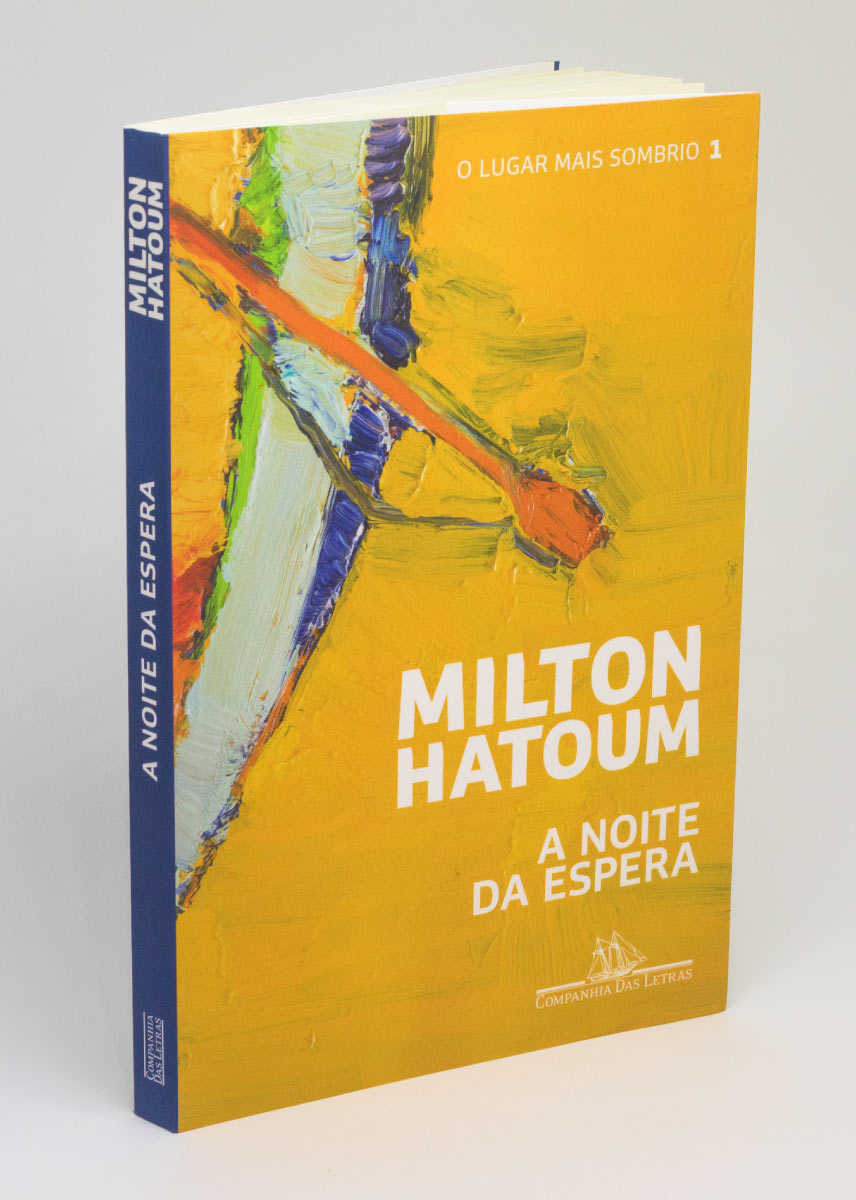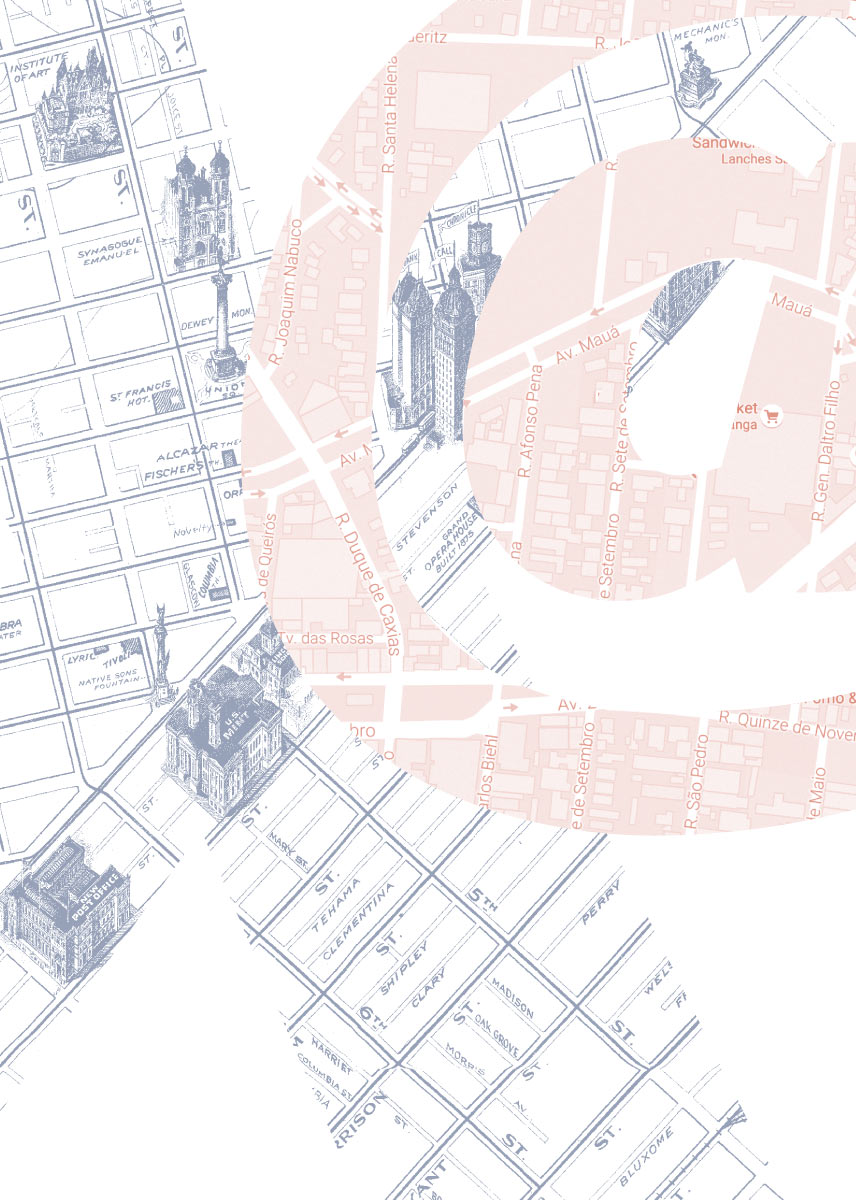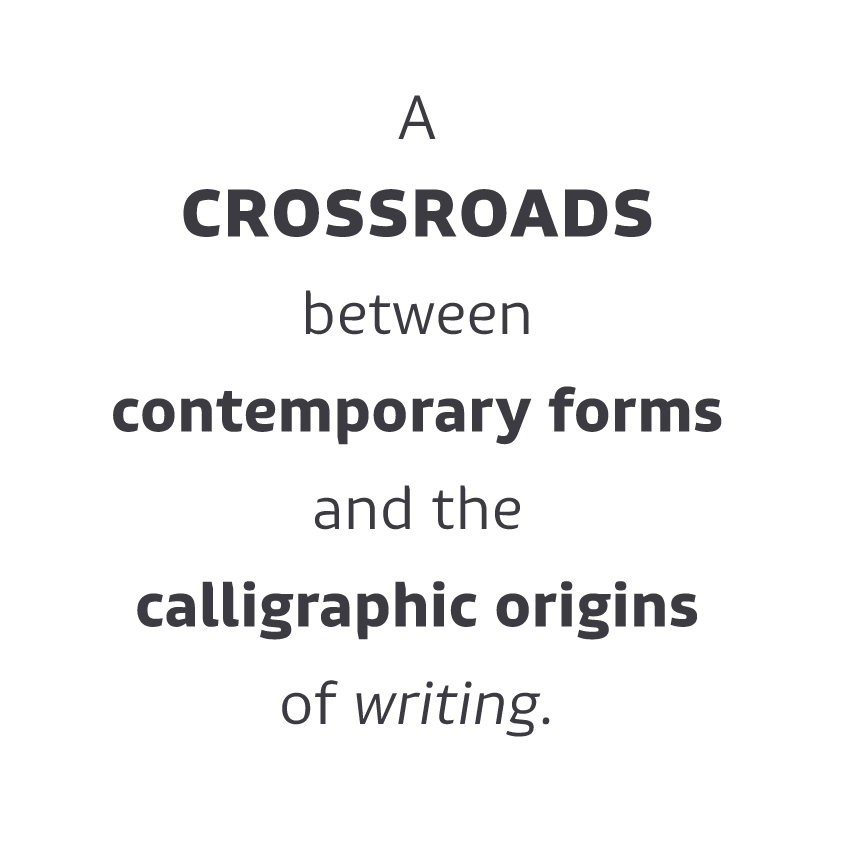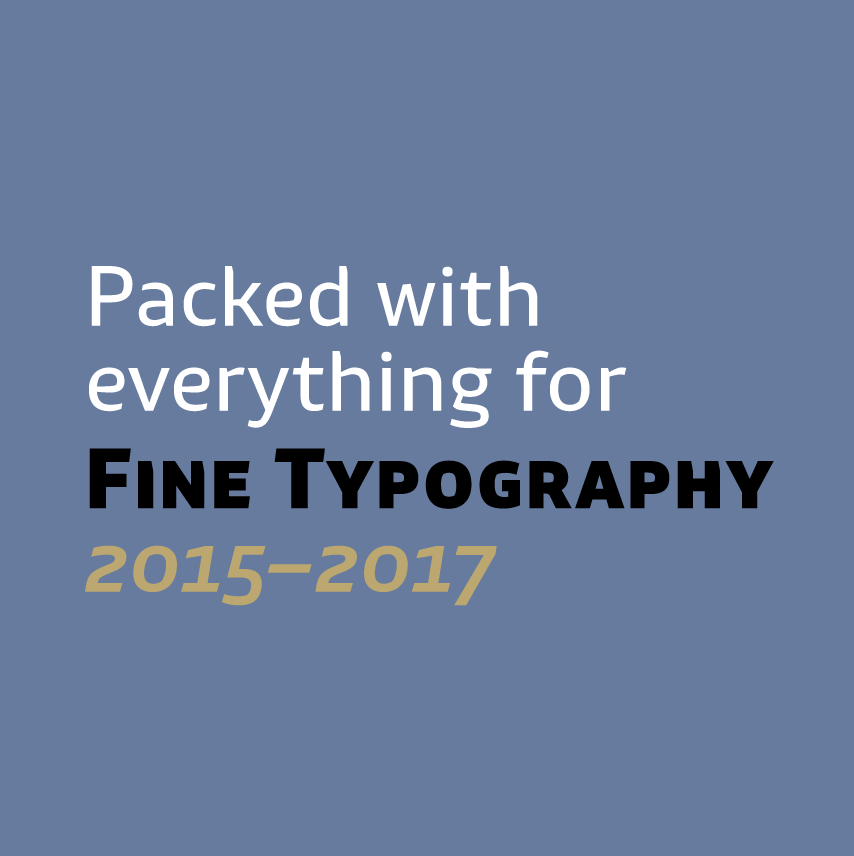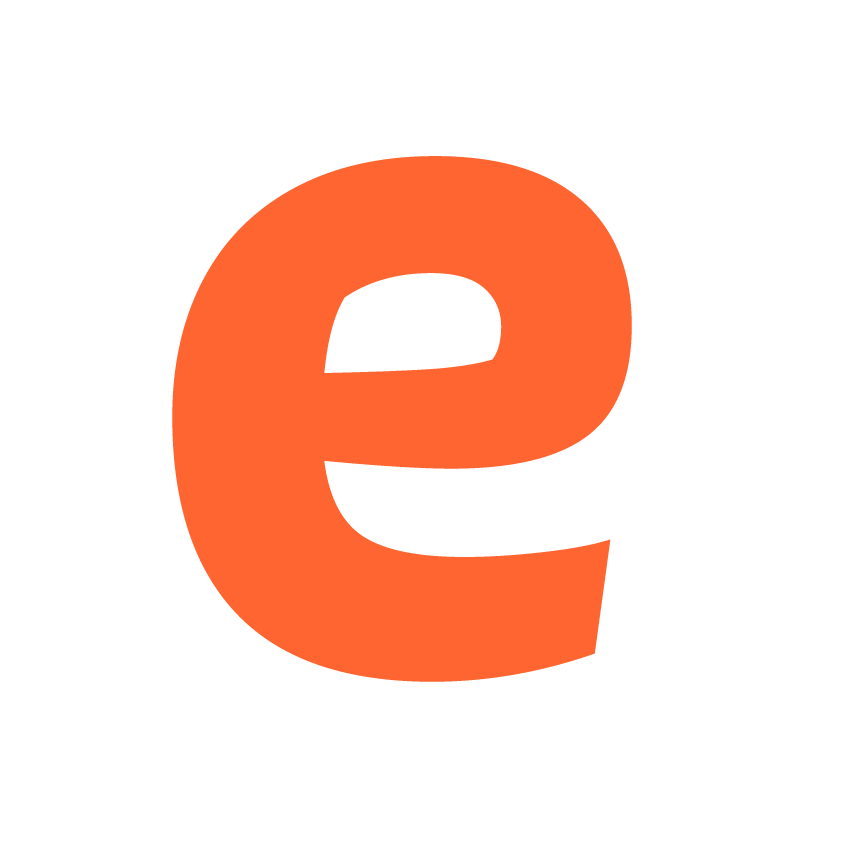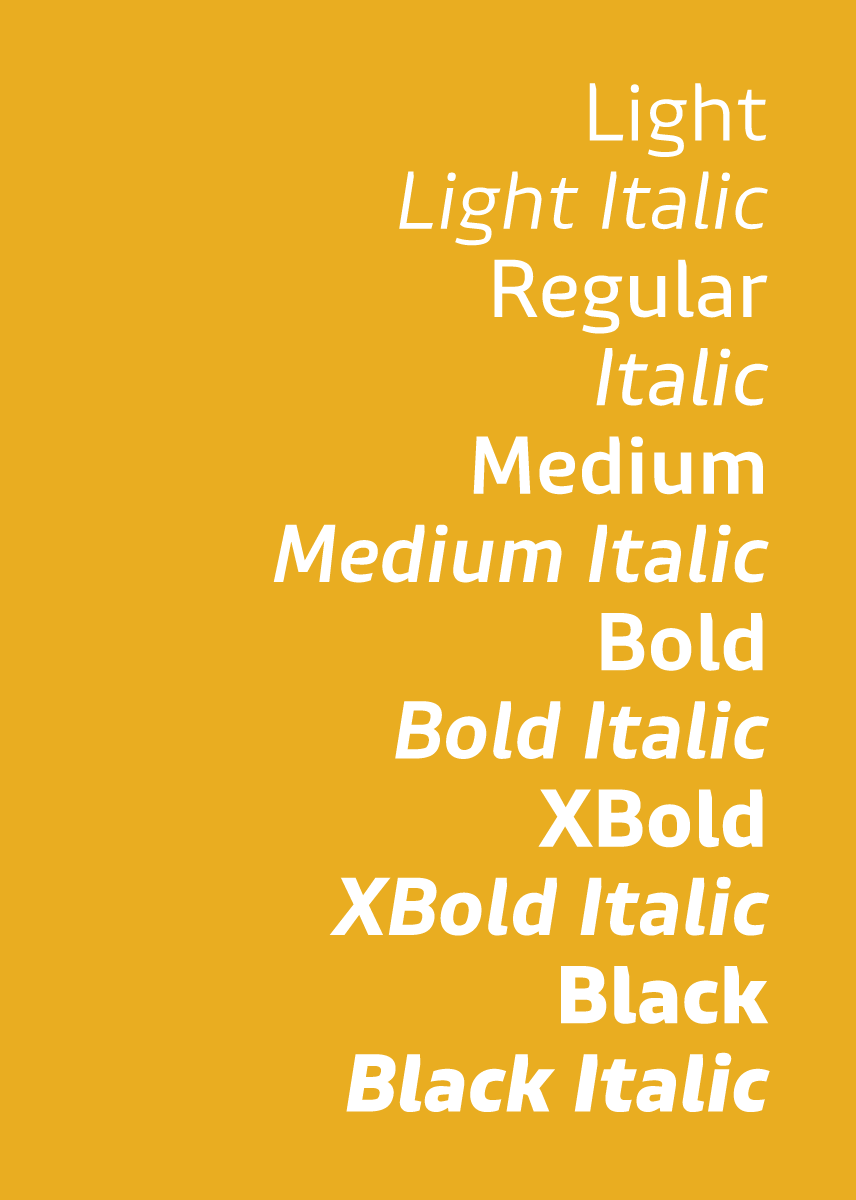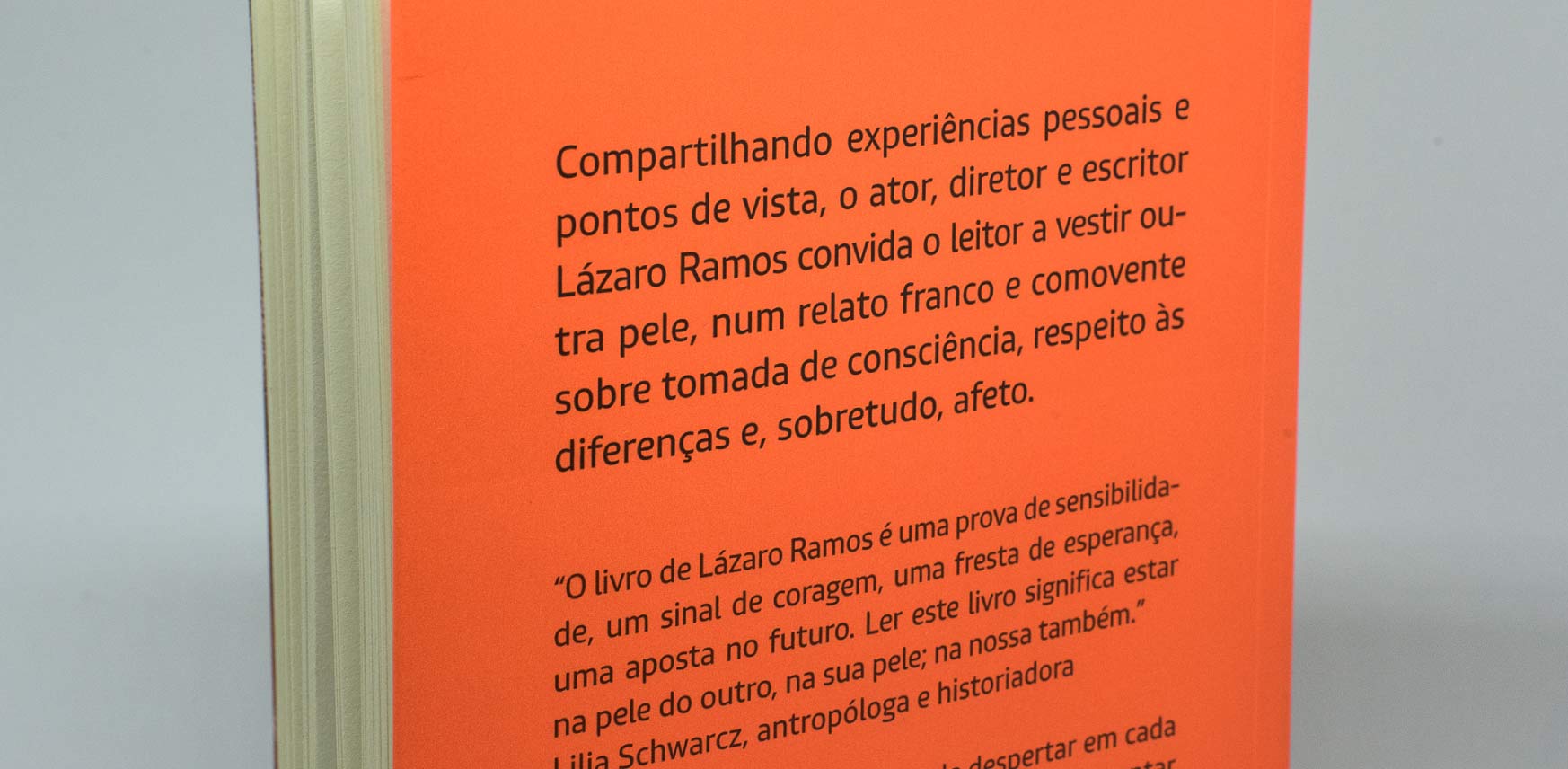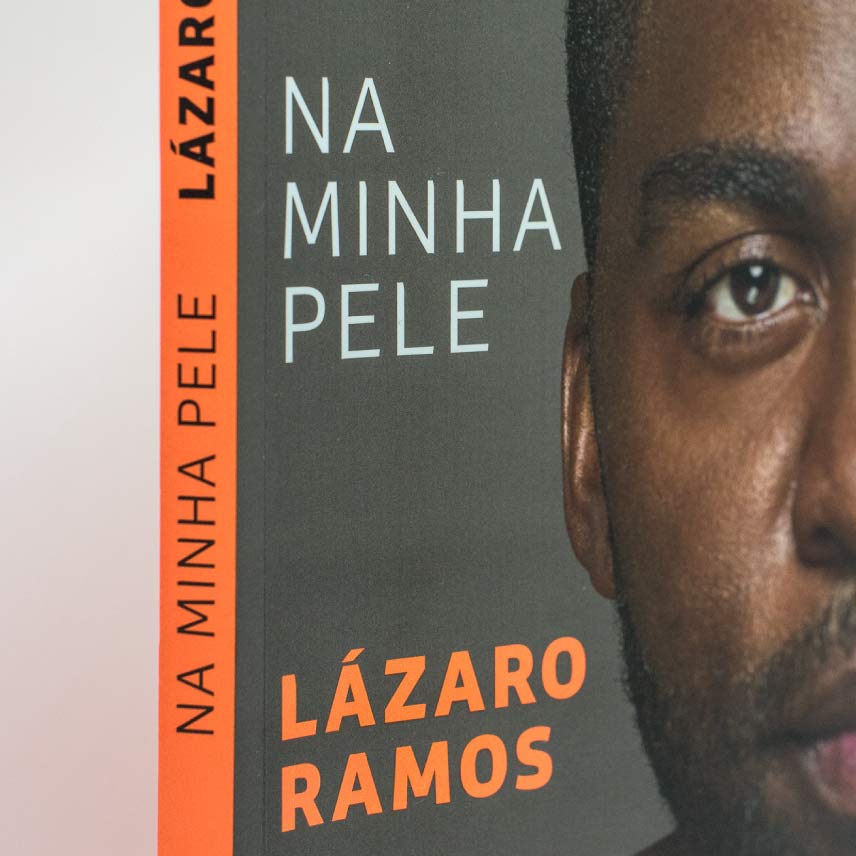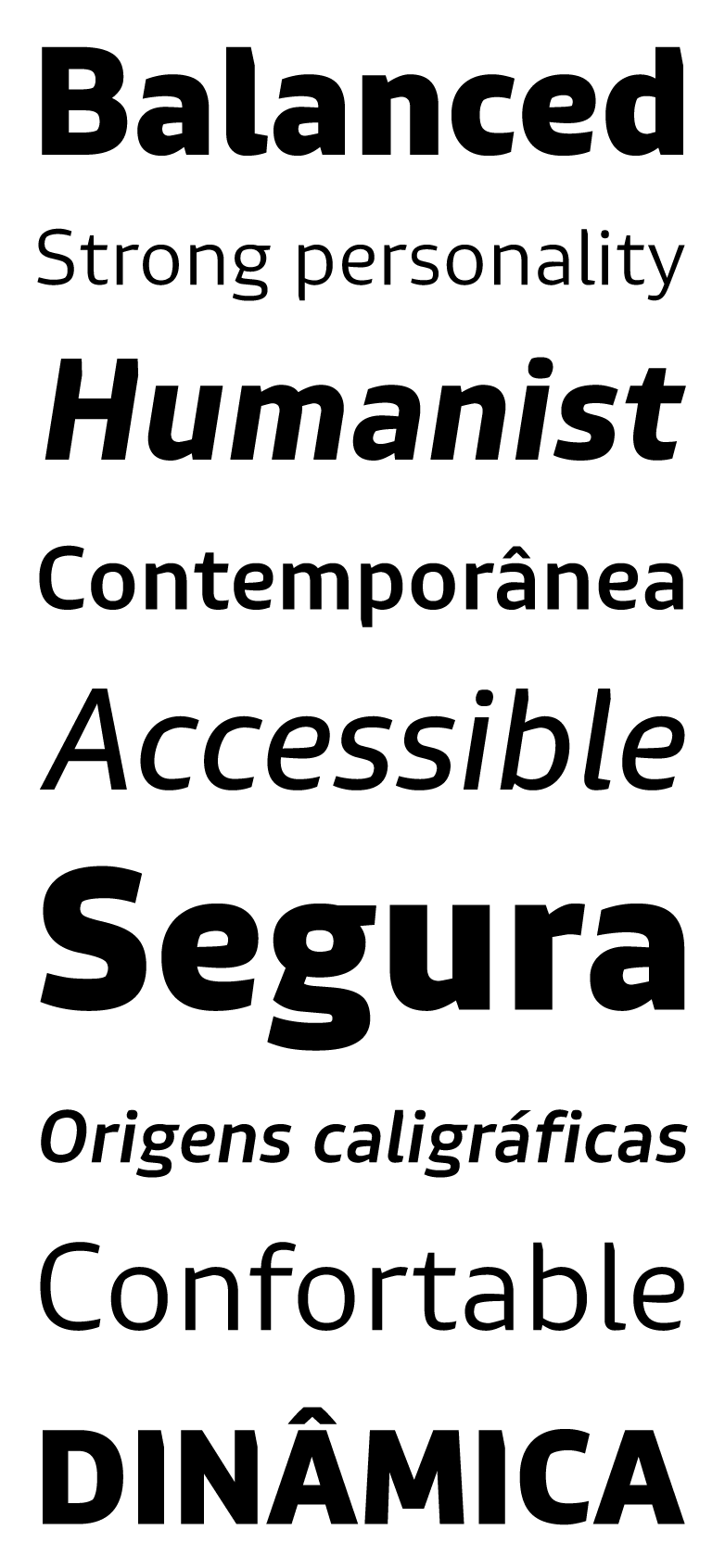
Lembra sugere o cruzamento entre formas contemporâneas e as origens caligráficas da escrita. Detalhes sutis da pena caligráfica quebram as formas limpas sem-serifas, criando uma sobreposição de expressões.Em tamanhos grandes, a fonte Lembra entrega uma expressiva personalidade, enquanto em tamanhos de texto, ela oferece uma confortável experiência de leitura; uma escolha ideal para projetos de branding, onde distinção e funcionalidade precisam andar lado a lado.